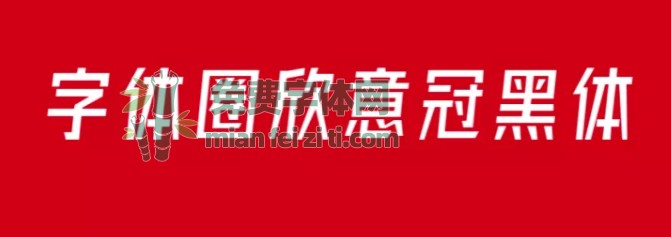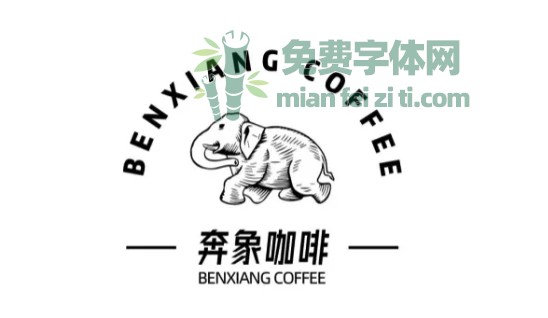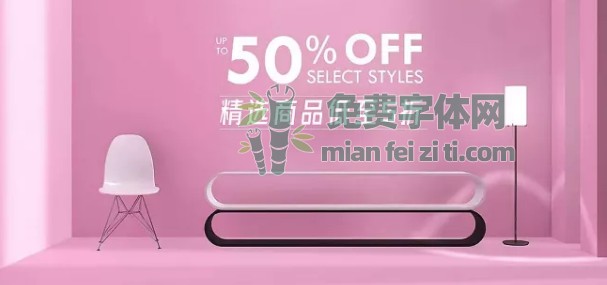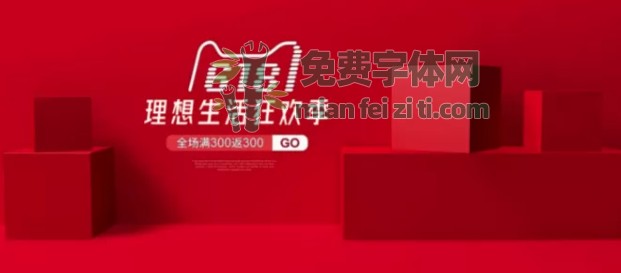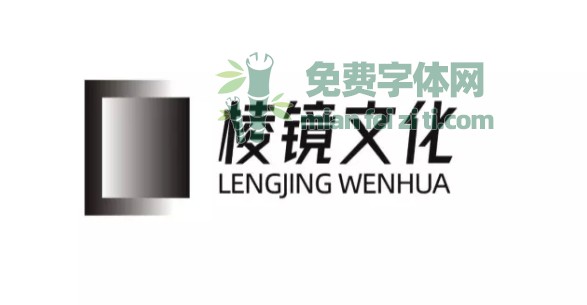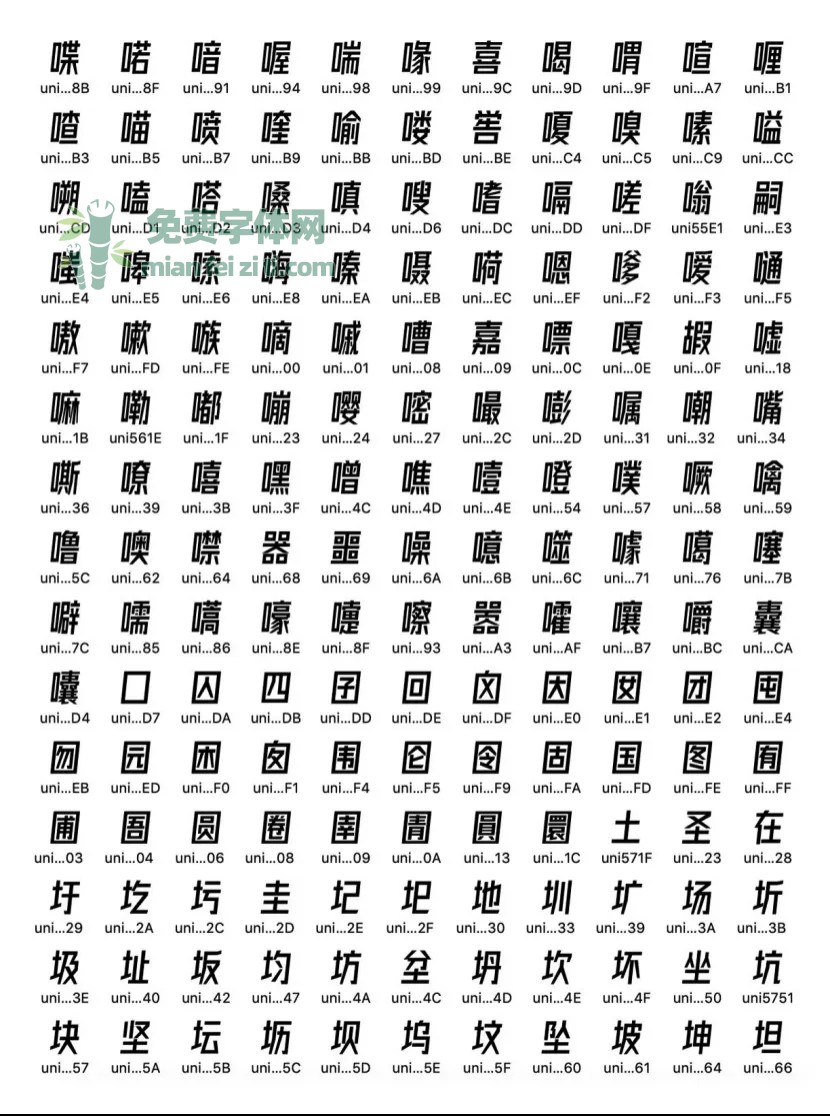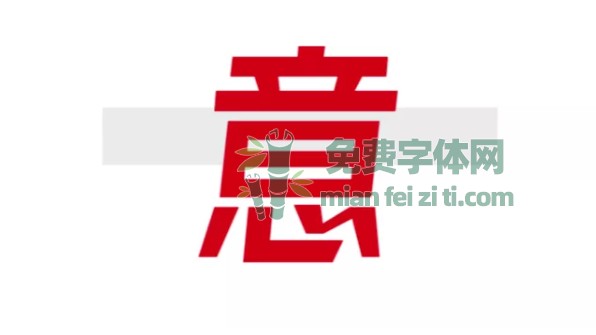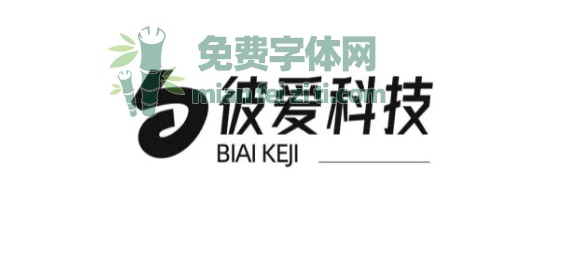
字体圈欣意冠黑体即将免费商用发布!
大家好,我的一套免费商用的字体,正式跟大家见面了,本文虽不是什么励志的文章,但还是希望你能看完。
我在2018年已经有做套字体的想法,当时初步的做了上百个字形。当时说希望能尽快跟大家见面,虽然现在这套字已经不是当时那套字。
2019年,我创办了字库品牌(左字zofont),因为产能太低还没开张,一年最多就开发一两套字体,还不一定有人喜欢,但其实我挺喜欢做字的,这一年我也做了好几套字体。
这是一套倾斜类字体,同类免费字体还有前几月优设网发布的《优设标题黑》,这套字很优秀,短短几个月到处都能看到它的身影。
这套字叫《字体圈欣意冠黑体》,欣意=心意。对于这套字体的发布,不希望只限于这是一套字体,我更想纪念一件事情,那就是今年的疫情。我想以我专业技能为抗疫发声,希望疫情能早点退去,早点让祖国,让世界恢复往日的繁华。
这套字从开始设计到修改到最后开发,用了将近一年的时间(字形设计制作6个多月,后期修改+开发3个多月)。这大半年里,我没睡几个安稳觉,凌晨三四点睡觉是常态,有时通宵然后去洗个澡继续。
从决定今天发布到发布,就两天时间,其实内心是很忐忑的。在发布完预告时我就一直在刷新有没有人看,有没有人留言,非常紧张。在写这篇文章的时候,内心很激动,也很紧张,直到发布之前我还在逐字检查修改这篇文章。
花了这么多精力去做这件事情,也不知道我做的这件事对不对,不知道发布之后有多少人看,多少人留言,多少人赞赏,多少人转发,多少人使用,受多少人喜欢(因为综合阅读量都在100以下,所以很害怕刚发布就凉了)。每次出去看到广告上别人的字体,我就经常幻想着以后这里换上我的字体会是什么样。
字体应用展示